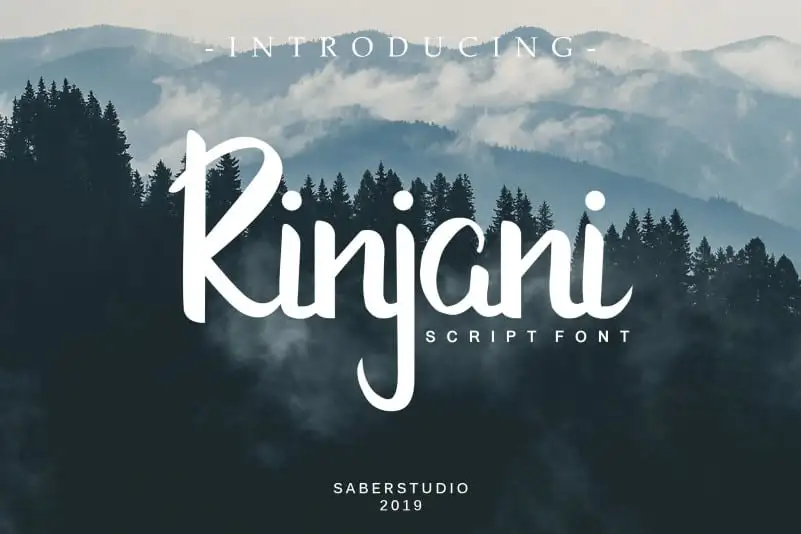
Rinjani Script Font é uma delicada e poderosa fonte tipográfica que traz um toque pessoal distintivo. Ideal para inspirar qualquer novo projeto design, essa fonte elegante vai tornar seus projetos únicos e atraentes. Desenvolvida pelo designer didiksaputra, Rinjani se destaca por seu estilo único, combinando perfeitamente com uma variedade de estilos de design, desde identidades visuais até letras e gráficos. Seja você um designer profissional ou iniciante em desenho, Rinjani Script Font é certamente a escolha ideal para suas necessidades criativas neste mercado vibrante e diversificado do design gráfico.